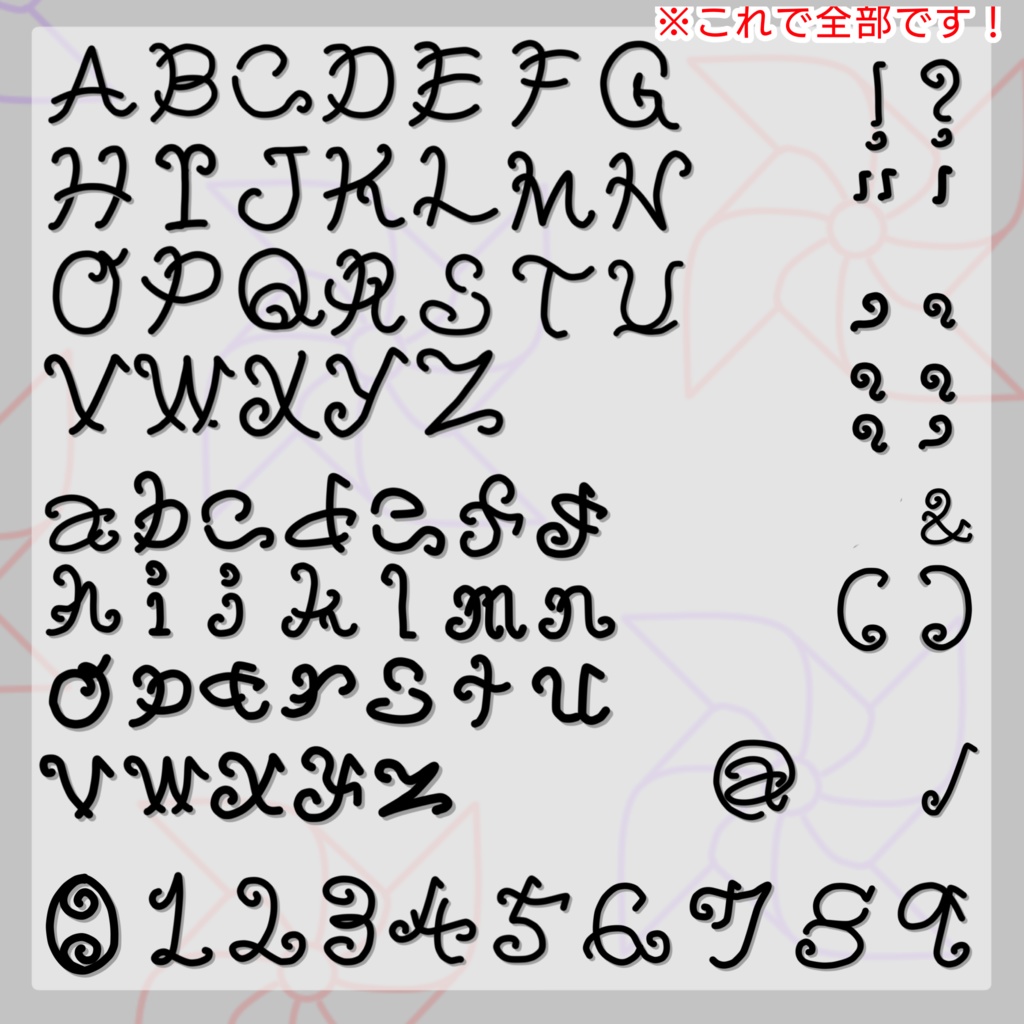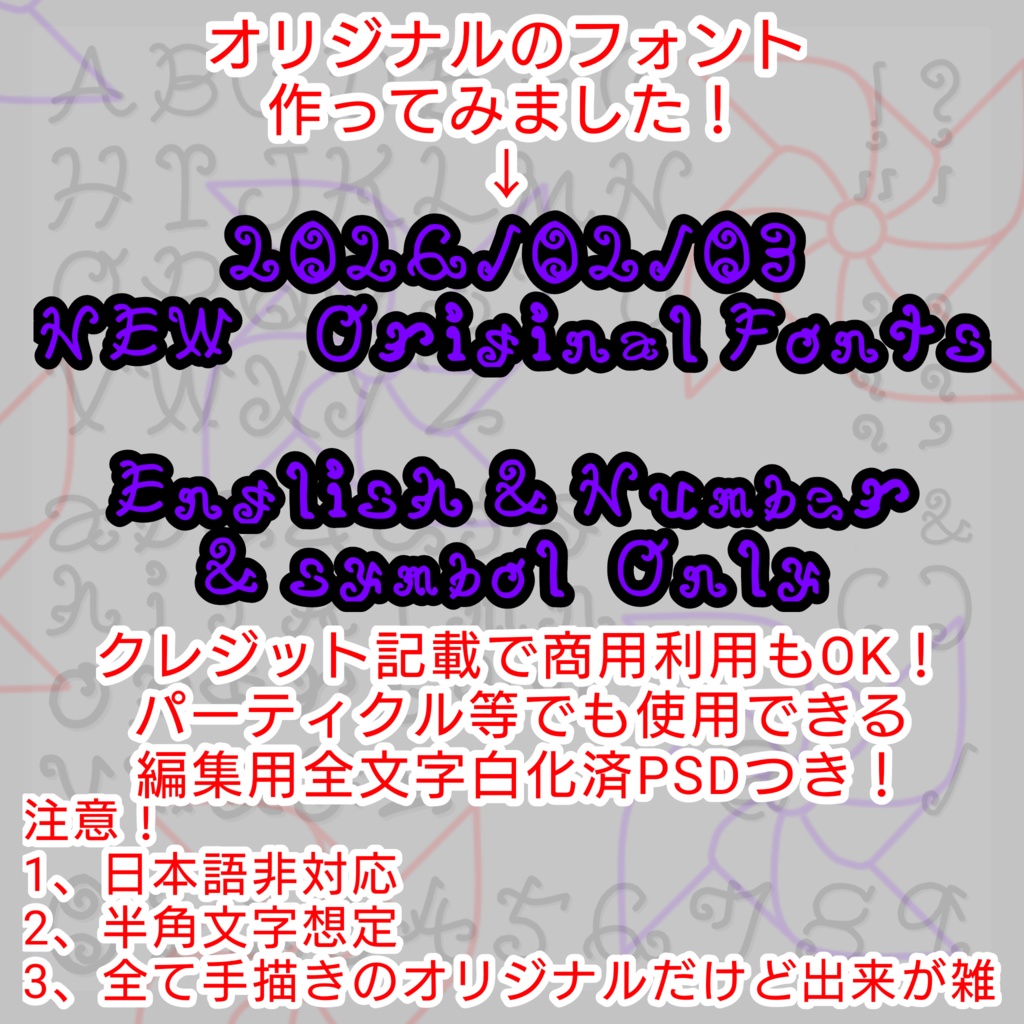
ボサボサ屋【CC0】【フォント】ぐにゃぐにゃり文字【無料】ダウンロード商品¥ 0無料ダウンロードぐにゃぐにゃり文字.zip (24.7 MB)ぐにゃぐにゃり文字.zip「ギフトとして贈る」とは一つ一つ丁寧にぐにゃぐにゃ手描きしたオリジナルフォントをスマホのみで作成。元個人用なので色々雑なのはお許しを!基本は半角で、全アルファベットと数字、URL記載に困らない程度の記号くらいしか作ってないので、日本語は非対応です。それでもよろしければご自由にどうぞ! 追記:サポートを止める代わりに著作権破棄し、CC0にしました。利用規約なんてものはありませんが、使用によるいかなる責任も私は負いません。 【更新履歴】 2026/02/03 公開 2026/10/25 CC0にしました。ボサボサ屋音楽(その他)【CC0】著作権フリーBGM集『平和を願う』【無料】ボサボサ屋¥ 0音楽(その他)自作フリーBGM集『和』【商用利用可】【有料】ボサボサ屋¥ 300音楽(その他)自作フリーBGM集 各3種【無料】【商用利用可】ボサボサ屋¥ 1003Dテクスチャ【無料版あり】自作マットキャップセット【商用利用可】ボサボサ屋¥ 1003Dテクスチャ【無料】ToonStandard想定ぬい風マットキャップセット【商用利用可】ボサボサ屋¥ 03Dテクスチャ【無料】ケモ用体毛風マットキャップ【liltoon&ToonStandard想定】【商用利用可】ボサボサ屋¥ 03Dテクスチャ【一部無料!】髪用マットキャップ+ノーマルマップセット【liltoon&ToonStandard想定】【商用利用可】ボサボサ屋¥ 500もっと見る